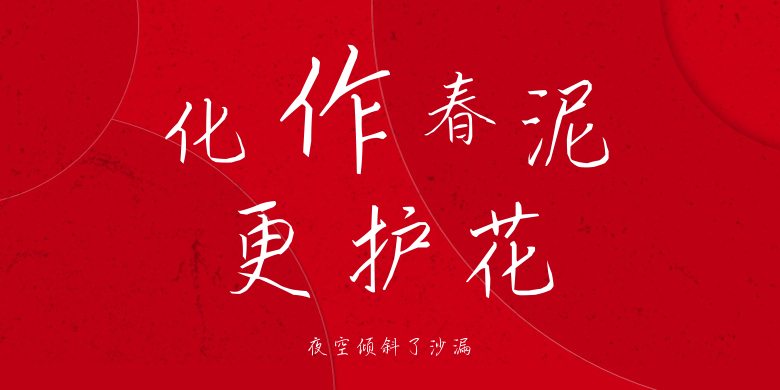
夜空倾斜了沙漏
夜空倾斜了沙漏,这款字体结构工整、笔画清晰,兼顾美观与易读性,适用于标题、正文、海报、包装、LOGO 等多种场景。字形优雅稳定,风格百搭耐看,适配日常排版与创意设计,让文字呈现更舒适、更具质感。夜空倾斜了沙漏一笔一画,皆是细节,以均衡的比例、流畅的线条打造舒适视觉体验,字形端正大气,风格简约现代。无论是商业设计、品牌宣传还是日常排版,都能轻松驾驭,让文字更有格调与力量。夜空倾斜了沙漏字体下载。